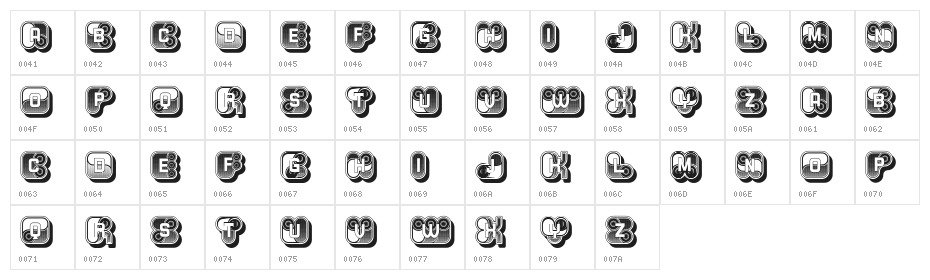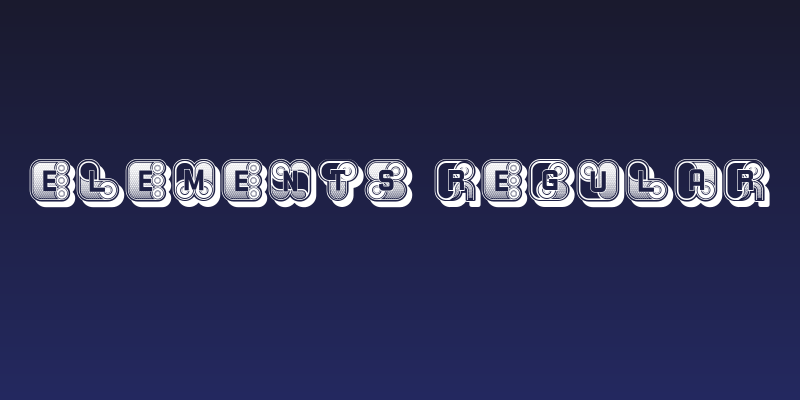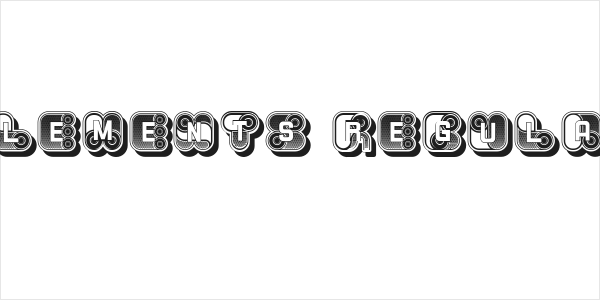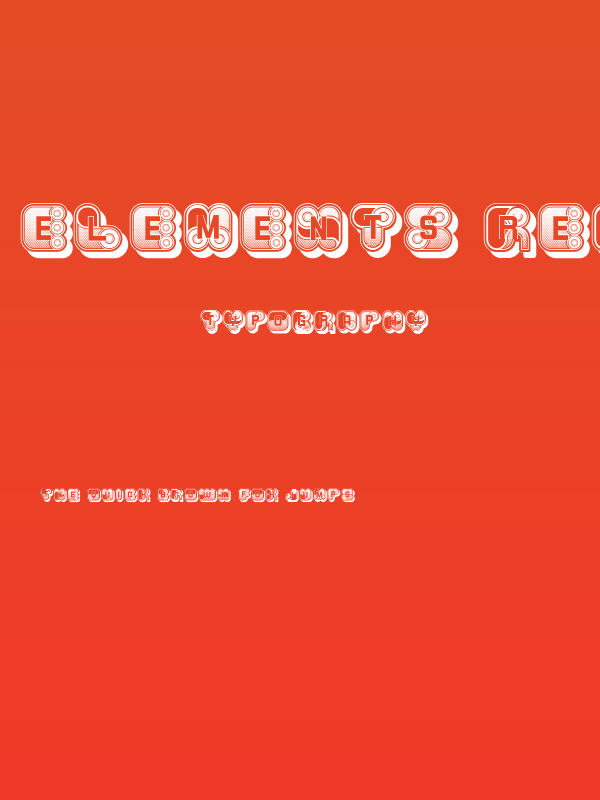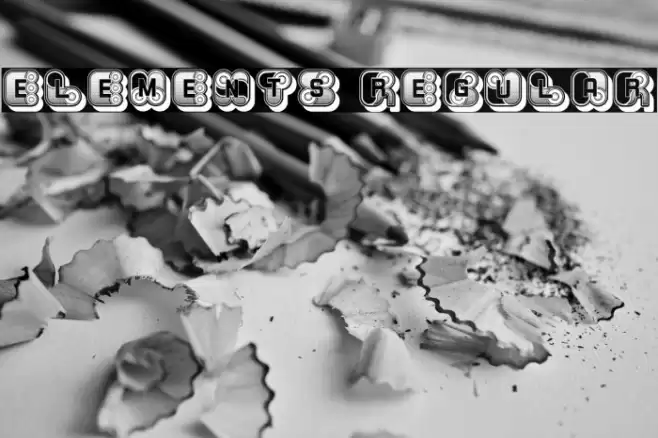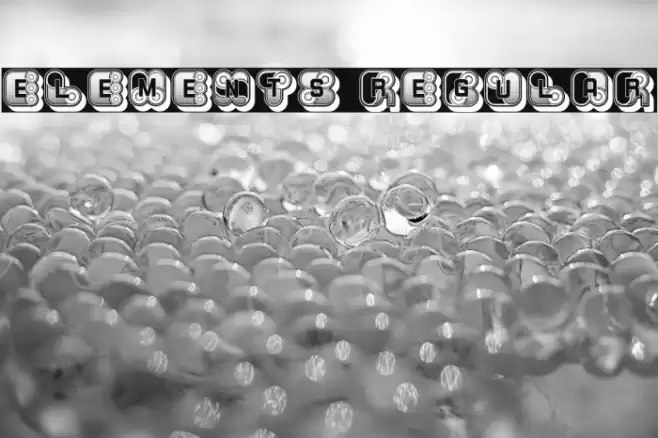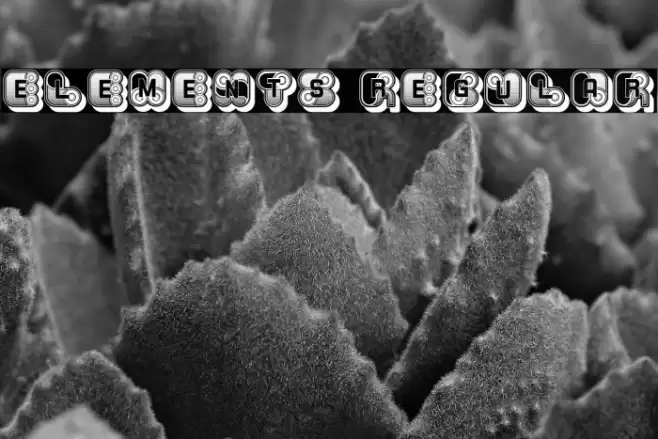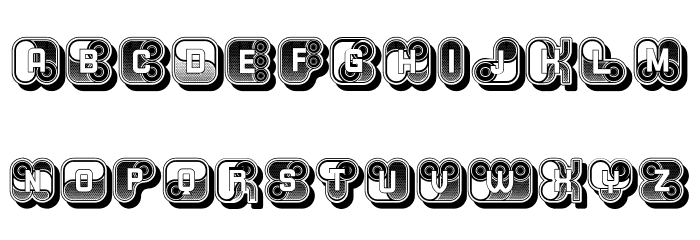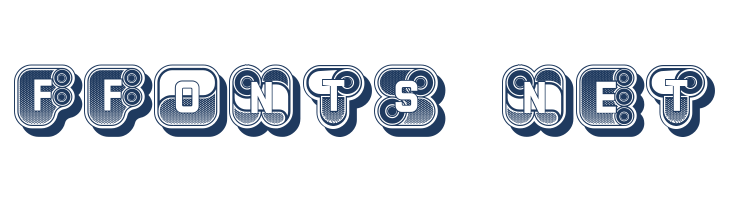
Elements Regular Font
| Рекомендуемые проекты | Ideal for posters, album covers, event invitations, and branding materials where a bold statement is needed. |